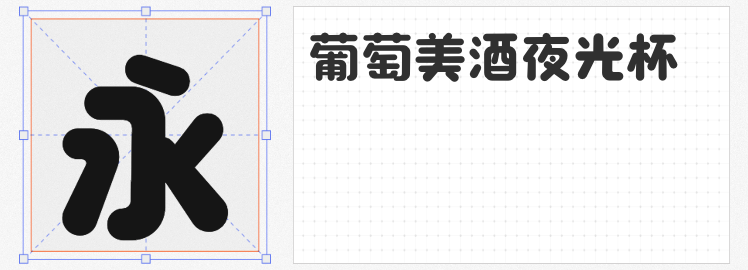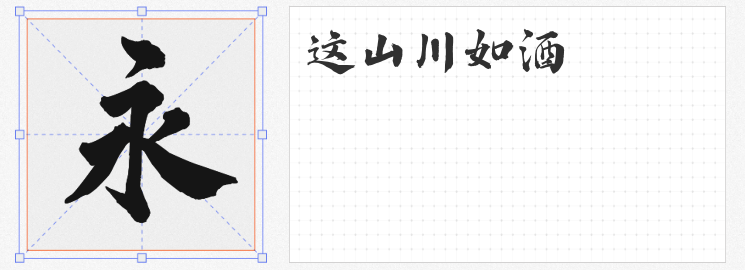
父亲节将至,如何用设计传递深沉的父爱?字体作为视觉表达的核心元素,既能承载文化底蕴,又能传递情感温度。今天推荐四款各具特色的商用字体,它们以独特的笔触与气质,为父亲节设计注入别样力量。
1. 造字侠磅礴简繁
这款字体以“中正”为魂,运笔如山峦起伏,一波三折间尽显节奏之美。粗细对比强烈的笔画,搭配略带飞白的质感,仿佛父亲宽厚手掌的温度与岁月沉淀的沧桑。方圆转折的巧妙结合,既有传统书法的端庄,又不失现代设计的张力,适合用于父亲节贺卡、品牌标语等场景,传递稳重而富有力量的父爱形象。
2. 造字侠侠义简繁
若说磅礴是父爱的山,侠义便是父爱的海。这款字体以圆转笔触替代方折,勾挑牵丝间如父子间的默契对话,潇洒中暗藏温情。其狂放而不失平稳的笔势,恰似父亲外表坚毅、内心柔软的双重特质,适用于父亲节主题海报、短视频字幕,以流动的线条勾勒父爱的深沉与包容。
3. 造字侠热辣隶简
这款创意隶书以“庄重威严”为基底,却通过简化笔画、强化横笔对称与竖钩直线力量,赋予传统隶书现代生命力。扁宽的中宫结构带来视觉冲击力,而撇捺的细粗过渡则如父亲严厉与慈爱的平衡。无论是文化产品包装、国潮风格海报,还是教育类品牌设计,它都能以“历史感与现代性并存”的特质,诠释父亲角色的厚重与传承。
4. 创客贴葡萄体
若想为父亲节设计增添一抹温馨,这款圆体字体是不二之选。圆润的笔画如葡萄般饱满可爱,既弱化了传统字体的锐利感,又以柔和的视觉语言传递亲子间的亲密无间。适用于儿童向父亲节礼物包装、亲子活动海报或社交媒体表情包,以轻松风格打破父爱的严肃印象,让爱意更显灵动。
从磅礴的笔力到圆润的童趣,四款字体以不同姿态诠释父爱的多元面貌。无论是庄重、潇洒、传承还是温情,它们都能通过视觉语言与设计场景深度融合,让父亲节的设计既有文化厚度,又不失情感温度。选择一款与品牌调性契合的字体,或许正是向父亲表达心意的最佳方式。